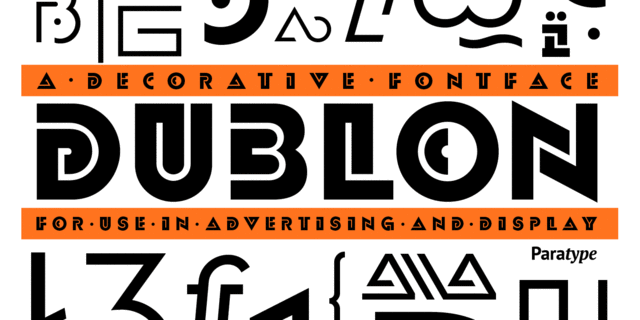
Гарнитура разработана для фирмы ПараТайп (ПараГраф) в 1994 на основе оригиналов шрифта украинского дизайнера-графика Олега Карпинского (Винница). Предназначен для применения в рекламе и акциденции.